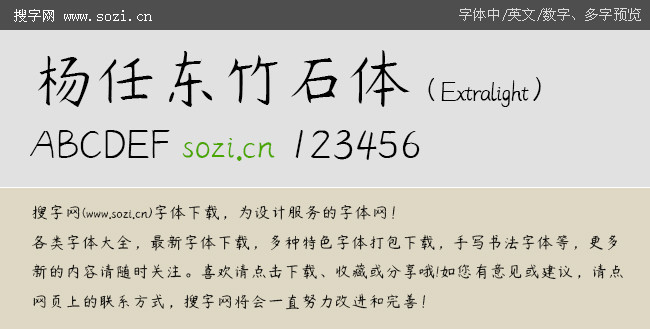
楊任東竹石體Extralight
搜字網給大家提供一款楊任東竹石體Extralight中文字體下載。楊任東竹石體于2017年4月26日世界知識產權日正式發(fā)布,本字體按照GB2312-80書寫,并增補了少量常見漢字;整套字體有7個字重,共計50000余個字符,本套字體授權全社會免費商用,意味著您可以將其無限制地捆入您的商業(yè)產品中,如海報、包裝、logo、網頁、APP等。